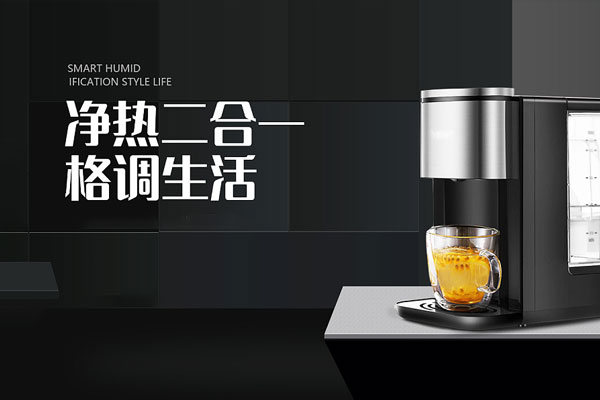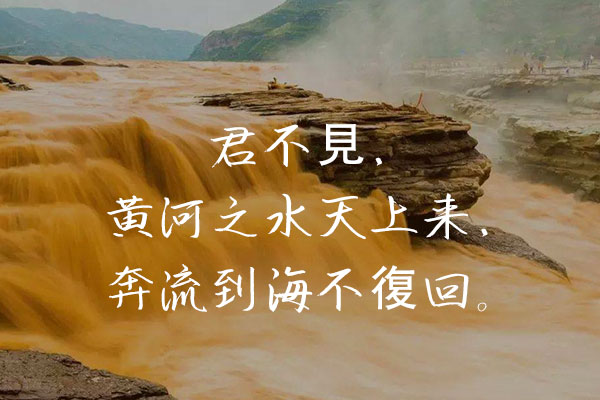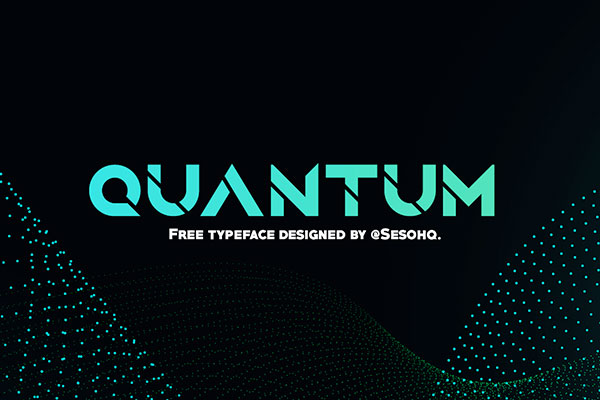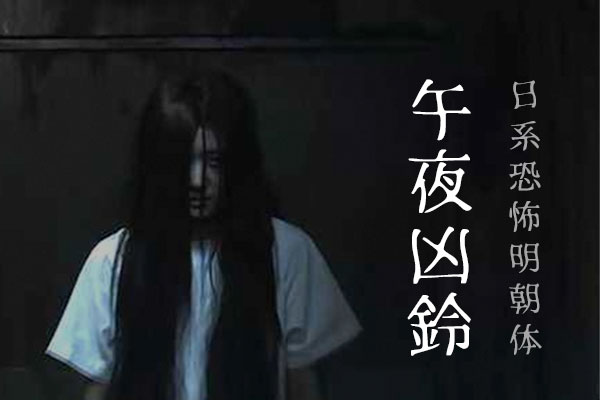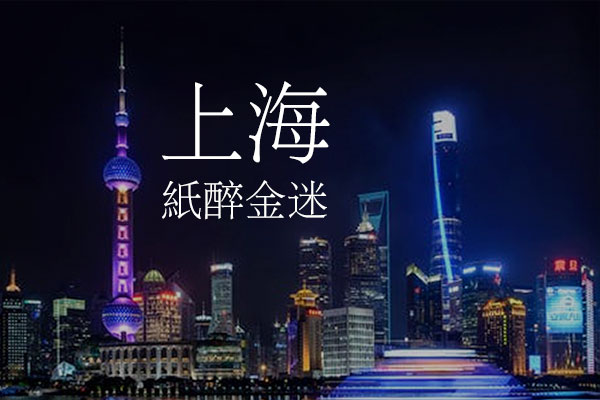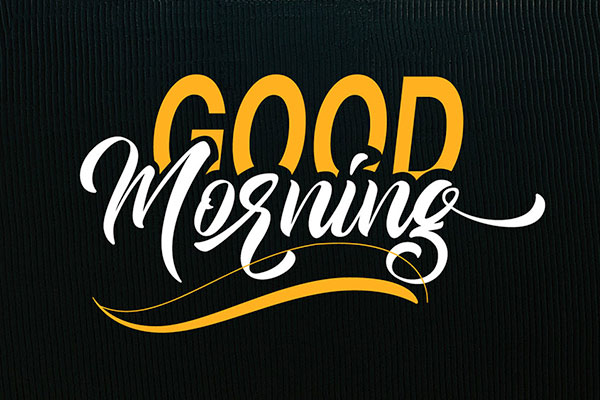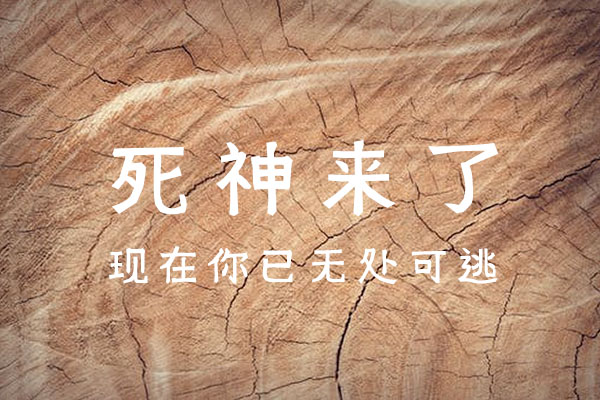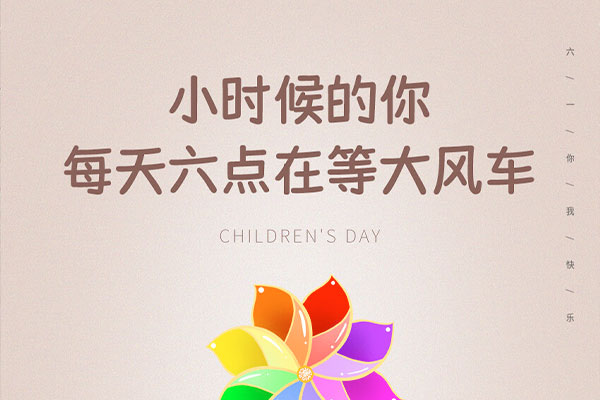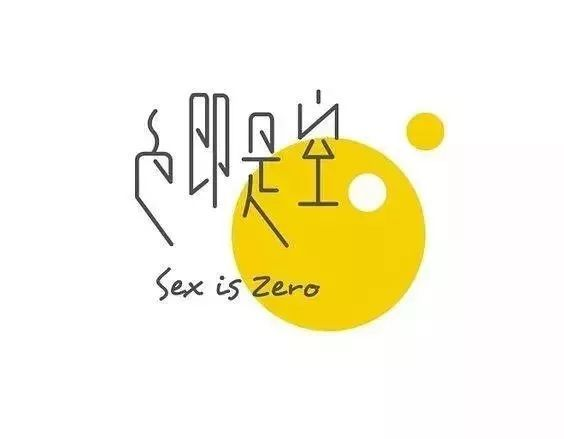
好字体到底是如何设计出来的
怎样做好的字体设计,大家来看看这些
1.确立一个概念
设计从创意开始。这可能是非常不确定的——"把这些信息畅通无阻组织起来非常重要。"也可能是有创意的设想——"如果这些饼干是用小精灵做的,可能味道会更好吧。"没有创意,就没有设计!
2.要沟通,不要装饰
经常说,形式在功能之后。这意味着两个方面。第一,每一个点、线、肌理、形状、色彩和图像都必须与表现的概念有关。第二,上述每种造型都应有一定的含义。如果仅仅因为你认为这个造型很棒而让它单独存在,那你就应该删掉它。
3.设计不是自娱自乐
设计的目的实质上就是为了大众接受:在为大多数人传达清晰的信息。你设计的图片越容易懂越好。
4.仅用一种视觉语言来表达
一个设计作品的所有组成部分都应在同一视觉水平上彼此关联。这就是说,为了表现出它们是某个统一信息的一部分,它们应该具有相似的特性。
5.能做到【少】,就不要做【多】
这是“少即是多”的另一种表达方式。一个普通的观众平均要接受多少信息、多少资料、多少令人厌烦的信息点(还不算那些垃圾信息)。那就按这个原则来进行设计吧。
6.要创造负空间,不要填满
尽管在设计中,围绕形状、图片和文字的空间看上去是空的,但实际上这些"空"也是一种形。设计这些空间的时候要仔细考虑好。这些负空间组合得越好就越有趣,整个构图也就更醒目。
7.分清主次关系
说到主次,先对一种颜色进行视觉强化吸引观众的注意力。然后用一系列的大小、重量、色彩的变化等,来引导观众。在重要的元素下划线或说明。如果观众分不清设计首先要突出什么,他们会因迷惑不解而离开。
8.小心对称关系
对称地组织材料会产生一种重复的、空间上静止的效果,违背了第18条规则。同时,对版式来说,对称意味着一件事:存在一个中心。这不能给观众带来任何新鲜的感觉。实际上,是版式设计了设计作品,而不是设计师设计了设计作品。
9.动静有致
视觉疲劳的解药是紧张,有一种很简单的方法,就是不断地改变视觉元素的大小、重量和空间,让它们看上去好像不停地变化和移动,这招很666666
10.按需要选取色彩
色彩感觉是主观的,这不全是猜测。色彩有其文化含义,而且彼此有其视觉联系。用以上这些“实际的”因素、有意义的方式,以及视觉上动态的方式来选择和组合色彩。
11.色彩越少越丰富
色彩感觉是主观的,这不全是猜测。色彩有其文化含义,而且彼此有其视觉联系。用以上这些“实际的”因素、有意义的方式,以及视觉上动态的方式来选择和组合色彩。
12.掌握明暗关系
在一个构图的不同区域完全改变明暗分布和明暗对比:清晰或刺眼,流动或朦胧,醒目或干净。
13.让字体具有亲和力
在选择文字的风格和大小时,要考虑用户的受教育程度,特别是用户的年龄。书写文字的存在就是为了传达信息,客户付酬给也是为了传递信息。如果这些信息无法辨认,不管什么原因,那这些文字就便没有意义。
14.最多使用两种字体
太多的字体只会让你误入歧途,甚至只注重形式。一次运用同一种字体类别,但有不同字宽字重的区别就可以了。
15.像对待图像一样对待字体
这是最难掌握的规律之一。字体也是一种图像,虽然看上去更像别的什么。此时更应考虑文字字体的视觉特性,与其他图像资料的关系,以及把它整合到整个构图中去。
16.用眼镜测量:设计是视觉的设计
我们的两个眼睛看到的东西可能跟实际有很大的不同。比如,一个实心的、平面的圆点和一个正方形,尽管实际的大小相同,但看上去却显得不同:因为点的轮廓是模糊而呈环状的,所以在面积上有收缩感。所有的视觉形式都是相互起作用的,你可以按照你希望的样子来安排。用目测:一般看上去更好。
17.创造图像,不选现成素材
随便找一些过时的照片,把它们按类型堆起来,这很容易。任何人都会做,很多人也是这样做的。但是至少应该把哪些找到的图像换成需要的图像,为客户,也为观众。
18.回顾历史,不重蹈覆辙
很多成功的设计都源自自以往的开拓者,以及所有人类努力的结果。要理解一个著名的设计是如何成功的,和照搬照抄可是两回事。可以借用其中的一部分,但不要在恭维和伪造间超越界限。
19.说真的,要忽略流行
现在什么最时髦?时尚很容易被忘记。100年后你的作品会被记住吗?时刻牢记着"无限"这个词,并在概念、含义、功能基础上,而不是在最新的、肤浅的时尚基础上做设计。
20.要果断,要有目的才做,否则不做
在设计安排上应避免犹豫。一种设计元素或另一种元素,一种方法或另一种方法,都应该清清楚楚。模棱两可可能有用,但即使如此也应是主动的效果,而不是因犹豫不决而产生的一个糟糕的副产品。